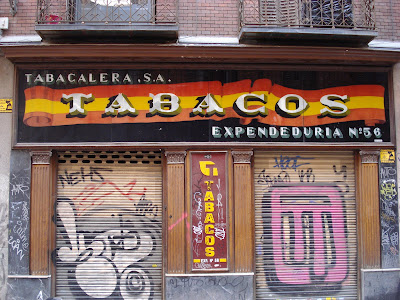
Restaurador Gregorio Gil
En Santa Engracia 112 y, dada la ruina del negocio, probablemente en trance de desaparición.
Autos Alcalá
En Alcalá 118.
Como curiosidad, comentar que fue la primera empresa española de alquiler de vehículos con y sin conductor, constituida en 1940.
Esta es su oficina central, aunque cuenta con otras delegaciones en Madrid.
Bar Martín
En Menéndez Pelayo 17, fue inaugurado en 1940.
Estanco
En la calle Palma 56.
Letrero comercial firmado por un tal M. Sanz y realizado con toda seguridad en la inmediata posguerra, cuando desde el gobierno se crearon los estancos en un nuevo impulso a la producción y consumo nacionales del tabaco.
Como franquicias que eran de un monopolio estatal, se les obligó a distinguirse con los nuevos colores nacionales, los de la repuesta bandera monárquica.
El negocio actualmente está cerrado.
Reparación Rápida de Calzado Luis
En la calle de Olid 14.
El rótulo, pintado a mano entre lo artístico y lo naif, aparece firmado, en su esquina inferior derecha, por un tal J. Gallo.